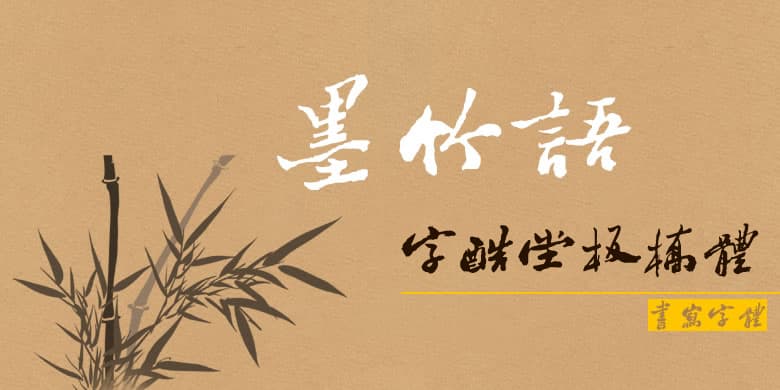
字体介绍 品牌:方正字库字酷堂设计师:过中运发行时间:2017字库编码:繁U(GB12345-90-U)分类:常规书写·毛笔字体属性:精品字 英文名称:ZKTBanQTFU.TTF 该字体源于清代书画家、“扬州八怪”之一郑板桥的书法及画作提款,并补充制作了大量缺字,汇成此字库。郑板桥的书法自称“六分半书”,介于楷隶之间,又参以行书及绘画笔法。这款字体的气质古怪清奇,视觉张力强,同时也氤氲着深厚的传统底蕴。适用于文化、商业类品牌的广告和产品包装设计。 字体下载 官方下载